小编个人非常喜欢的字体就是书法字体,但是现代的年轻人生活节奏太快了,没有什么精力去练习书法了,就连写字都变得很奢侈。所以即便是喜欢也不可能在这上面花太多的功夫,所以要用到书法艺术字体的话只能通过像字体视界这样的字体平台去寻找了。我们现在就来看看还有什么途径可以找到书法字体生成快速的办法吧。
原始的书法是用笔墨纸砚写出来的,黑白相配是最原始的美,写的好的书法充满了诗情画意。古代的东西总是那么的经典,流传至今仍然被大众所认可,即便是现代提倡环保,电子已经逐渐替代了纸质,但是还是有那么多的人愿意去学习书法,足以见得书法的魅力之大。
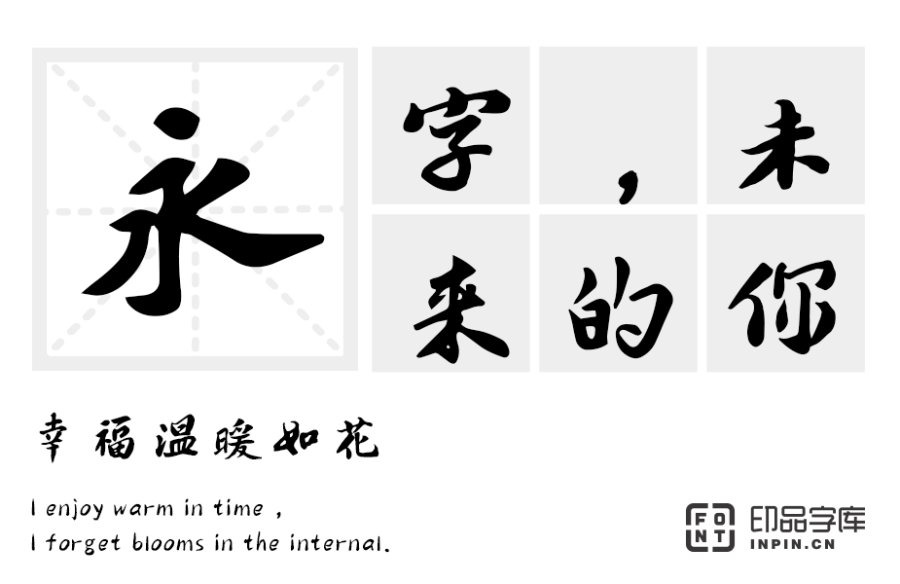
书法字体虽然现在大多数人接触的比较少,但是还是有很多的中国人甚至是外国人喜欢的,这种字体从古代流传至今都没有被时代淘汰就足以证明它是有自身的魅力的。现在还是有很多人愿意去学习书法,有一些大型场合也会用到书法字体。那么我们在没有专业的书法家的时候就可以用书法字体生成器去生成一种好看的书法字体,这样会很容易满足我们的需求。